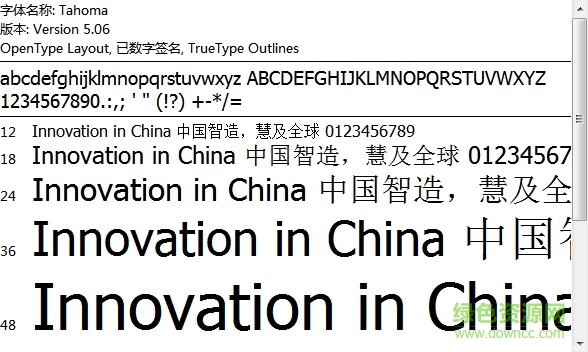
tohamattf字體是tohama家族系列英文字體,包括五個(gè)字重,字跡端正書寫流暢,讓人有著清晰的視覺呈現(xiàn)和嚴(yán)謹(jǐn)?shù)膬?nèi)容表達(dá),綠色資源網(wǎng)今日推薦!
tohama字體家族包括:tahoma、tahoma_0、tahomab0、tahomabd、Tahomaz等五種,字跡深淺明暗上均有不同的處理,讓用戶對(duì)中英文的修飾更加得心應(yīng)手。
tohama字體類似一款經(jīng)典字體,對(duì)文字的處理十分中規(guī)中矩,家族系列中包括所有的書寫方式,讓用戶用起來(lái)更為妥帖,給你的平面設(shè)計(jì)、包裝設(shè)計(jì)、藝術(shù)設(shè)計(jì)帶來(lái)獨(dú)特呈現(xiàn)!